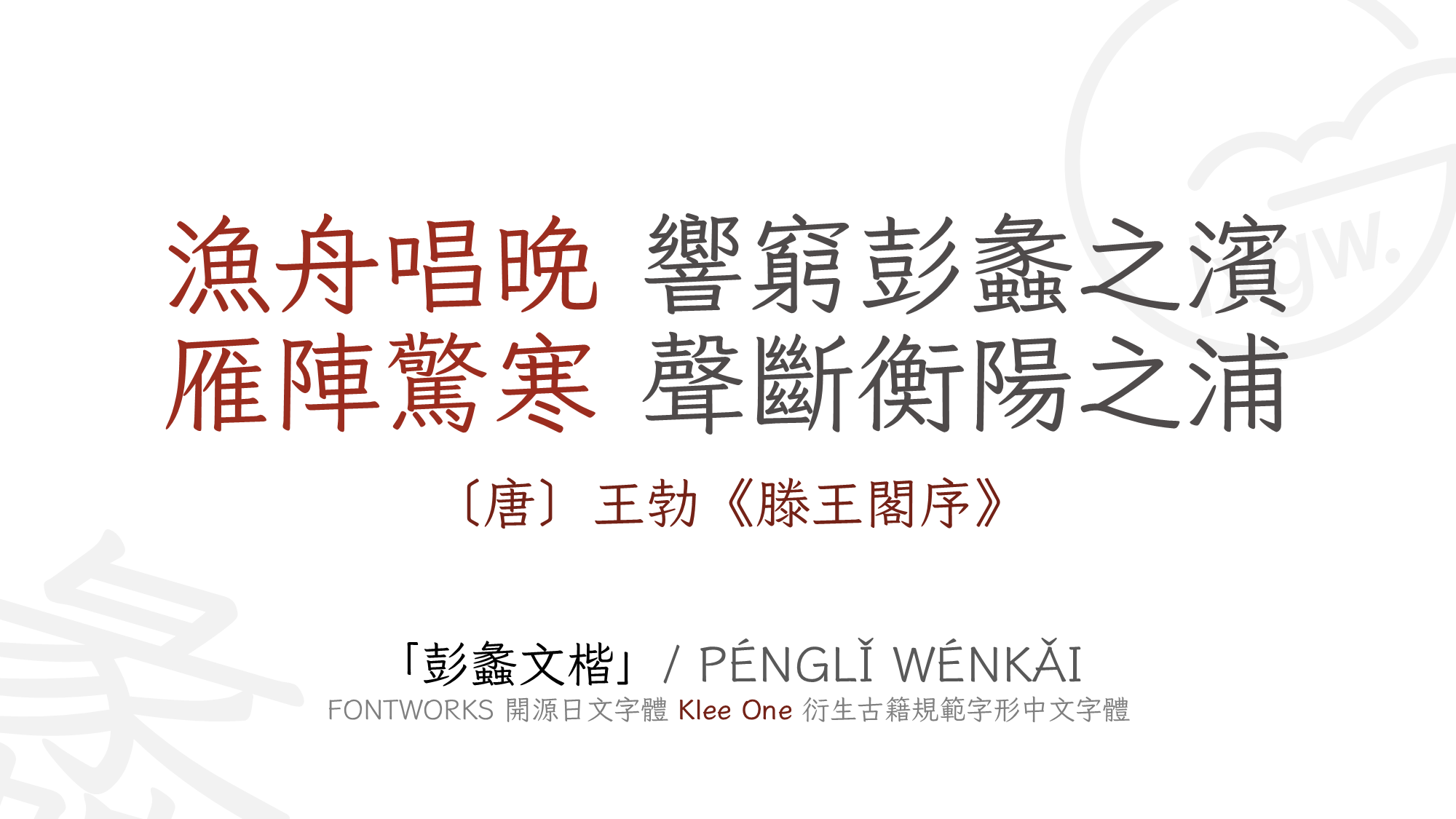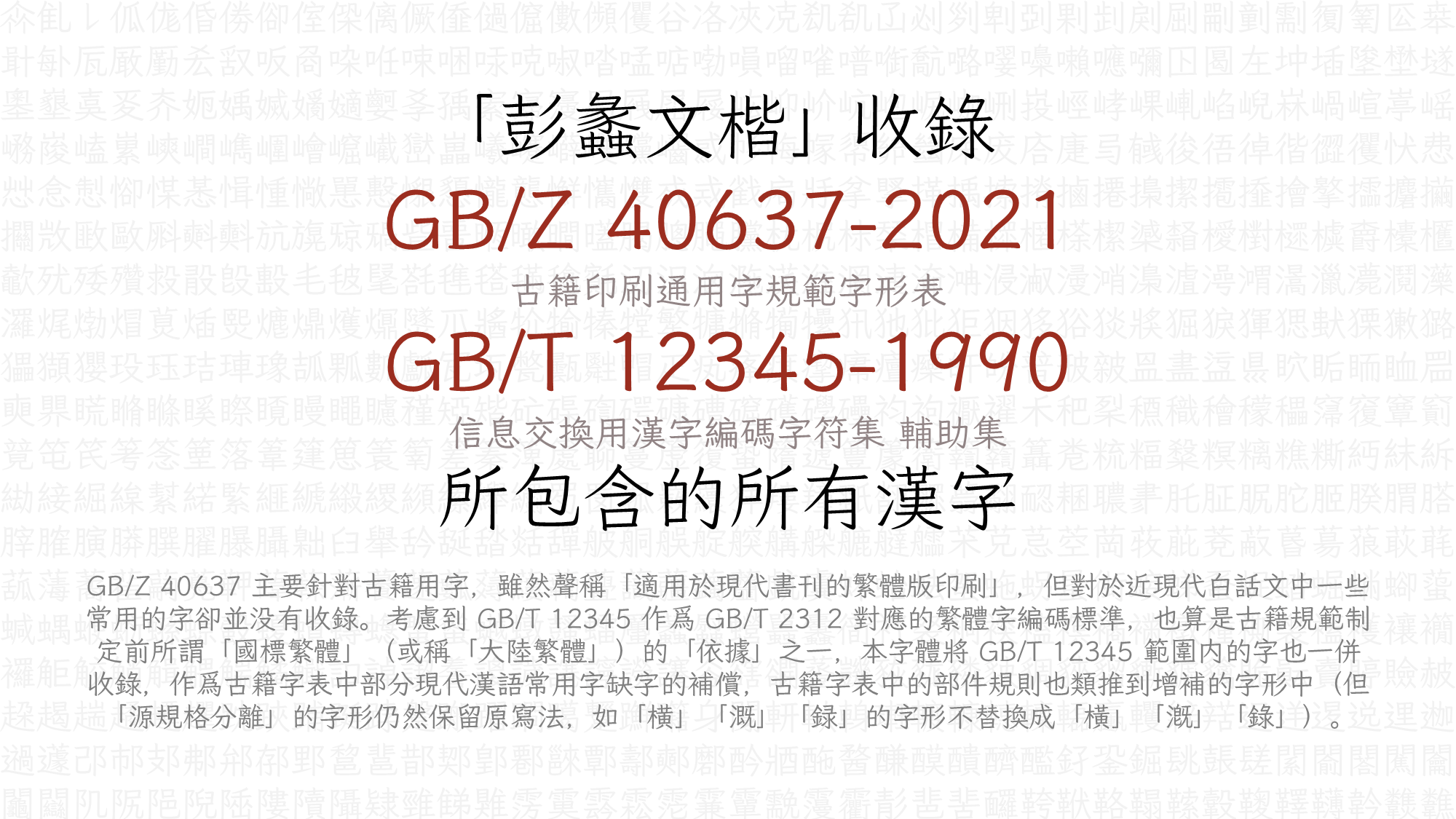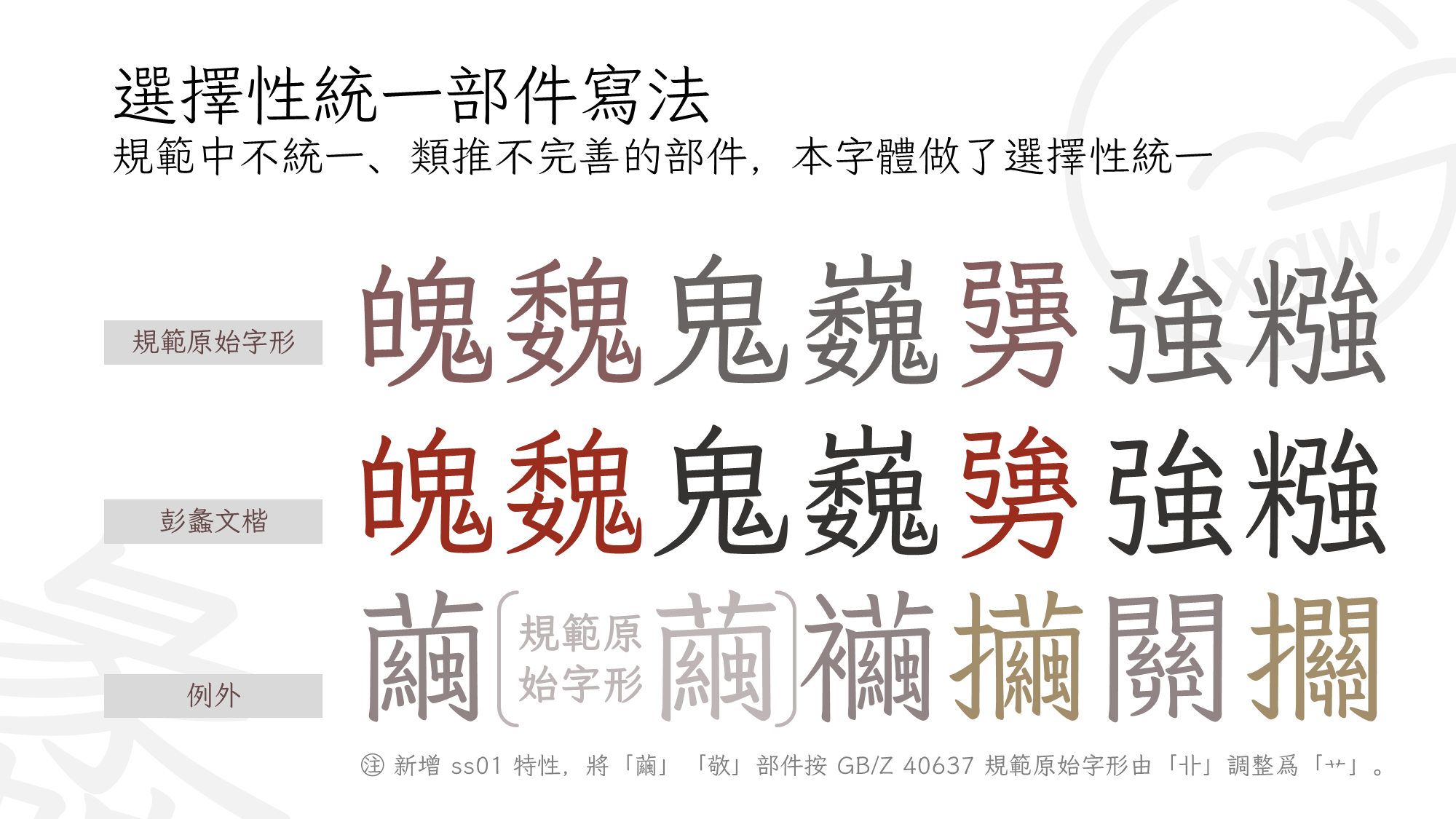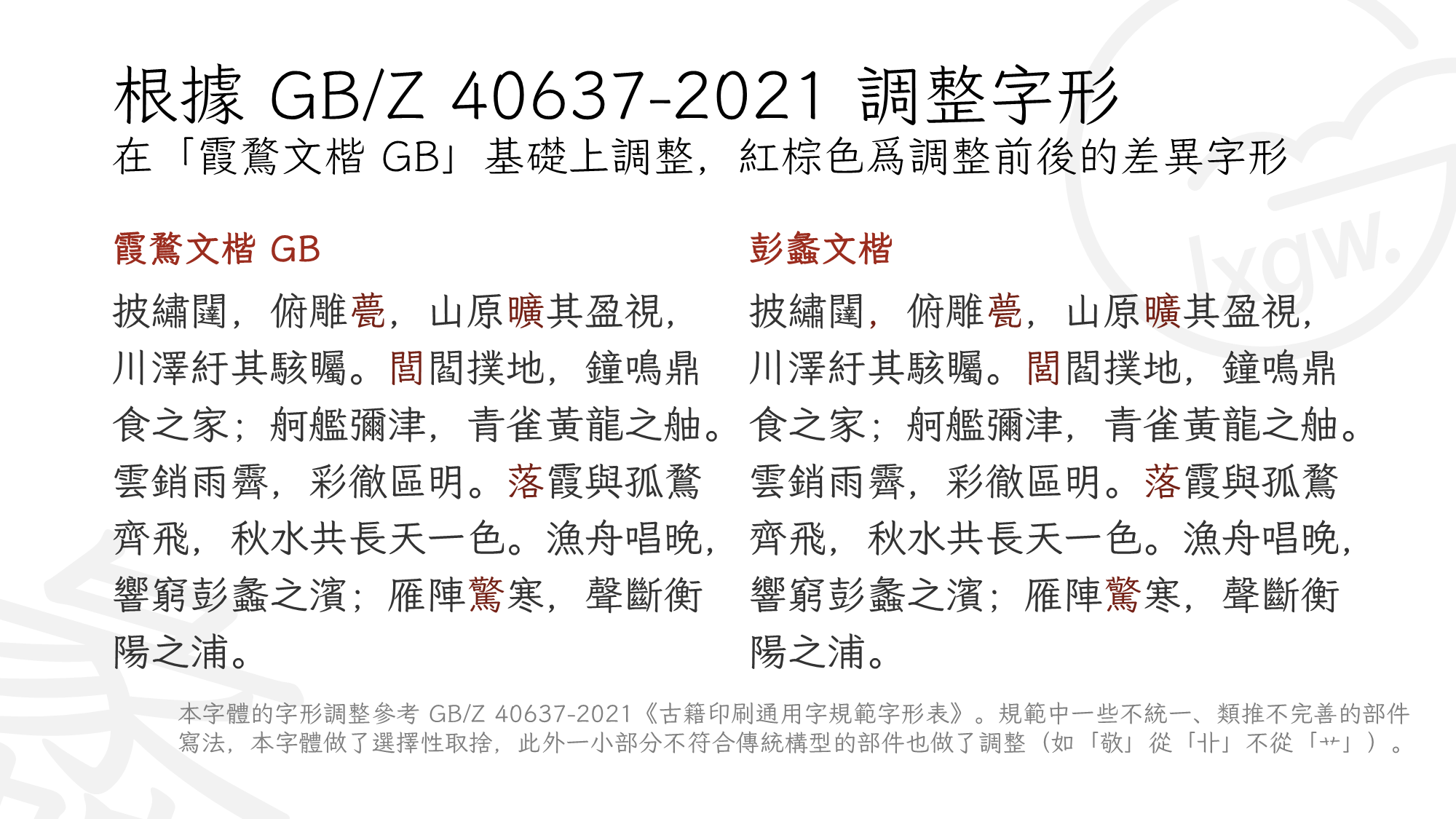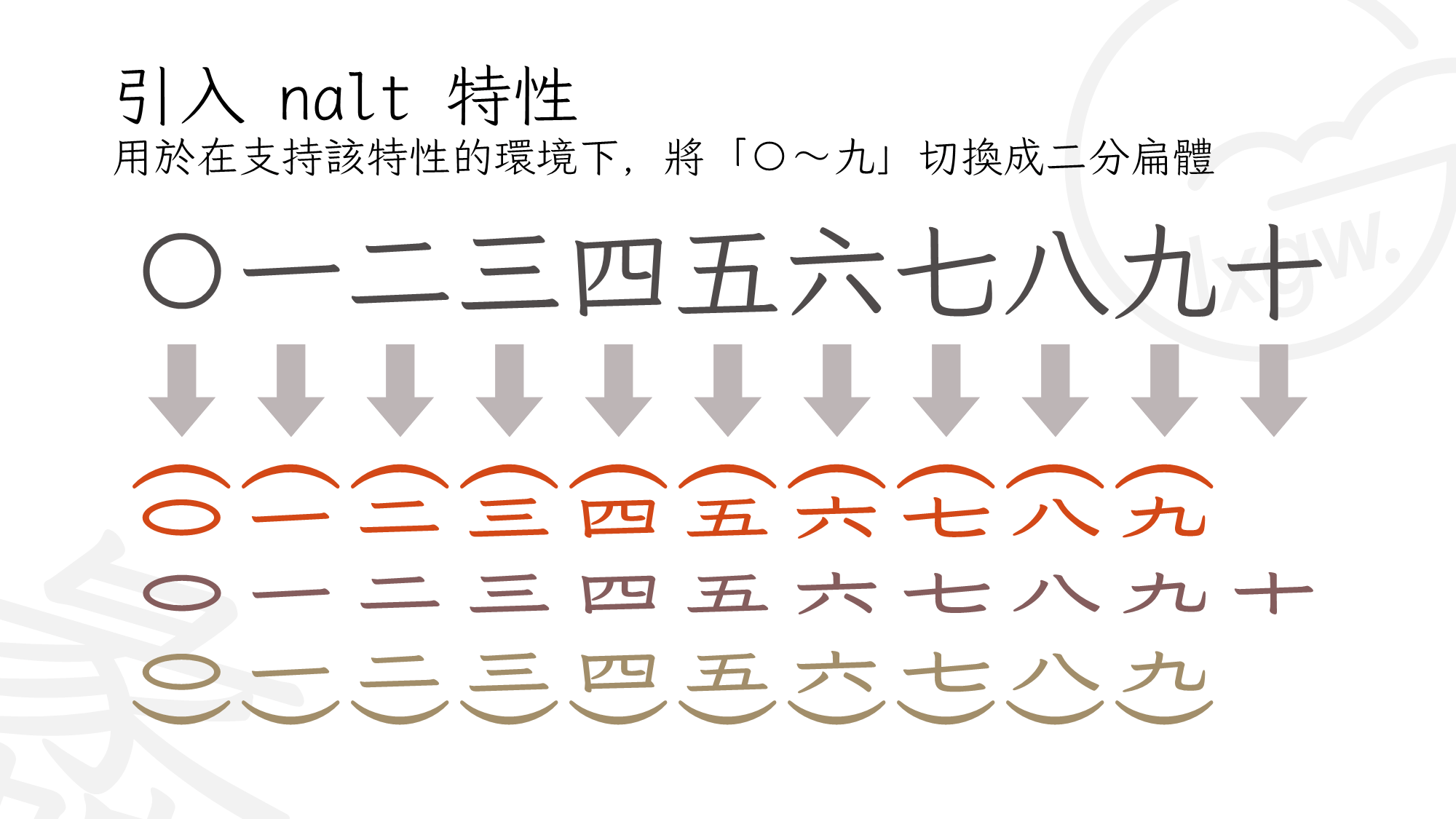
彭蠡文楷 / Pengli WenKai
基于《霞鹜文楷》系列字体衍生,参考《古籍印刷通用字规范字形表》(GB/Z 40637-2021)收字和调整字形的开源字体。
《彭蠡文楷》是基于《霞鹜文楷》系列字体衍生,根据《古籍印刷通用字规范字形表》(GB/Z 40637-2021)调整字形的开源字体,是 Fontworks(现日本蒙纳株式会社,Monotype KK)所发布的开源字体 Klee One 的三次衍生字体。
《古籍印刷通用字规范字形表》(GB/Z 40637-2021)是新中国成立以来对传世古籍印刷字的第一次整理规范,也是中国大陆第一部正式针对繁体字制定的字形规范。这部指导性技术文件声称「适用于传世古籍的印刷出版,以及现代书刊的繁体版印刷」,共收录了 14,250 个汉字字形,并提供每个字的首音和 ISO/IEC 10646 编码(涵盖 CJK 统一表意文字基本区和扩展 A、B 区)。 《彭蠡文楷》在 《霞鹜文楷 GB》 的基础上,收录 GB/Z 40637-2021 范围内的全部汉字,参考 GB/Z 40637-2021 所规定的字形进行调整,并对该规范中不统一、类推不完善的部件写法进行取舍。但愿这一开源字体项目,能为《古籍印刷通用字规范字形表》颁布后的实践贡献一份绵薄之力,为古籍印刷字体提供一种新的选择。
字体名称中的「彭蠡」一词出自〔唐〕王勃《滕王阁序》中「渔舟唱晚,响穷彭蠡之滨;雁阵惊寒,声断衡阳之浦」一句。 「彭蠡」为中国第一大淡水湖⸺鄱阳湖的古称(此外也曾作为巢湖的古称)。因「彭蠡」二字简繁无差,且与上游字体《霞鹜文楷》字体名称中的「霞鹜」二字一同出自《滕王阁序》,故本字体项目采用「彭蠡」作为名号。
「彭蠡文楷」支持 Unicode 变体序列(Unicode Variation Sequences, UVS),用于标点符号宽度和位置的选择, 点击此处查看一览表 。
• GB/Z 40637-2021 所收录的 14,250 个汉字,用于「传世古籍」所需汉字的排版与显示;
• GB/T 12345-1990 所收录的 6,866 个汉字,用于「现代书刊的繁体版本」所需汉字的排版与显示;
• Unicode 康熙部首区段所收录的 214 个部首字符,参考《康熙字典》总目中的部首字形进行取舍调整;
• 全半角 ASCII、拉丁补充-1 区、拉丁扩展 A 区、拉丁扩展 B 区、国际音标扩展区、拉丁附加扩展区、注音符号;
• 现代标点符号,以及古代汉语勾乙号「𖿢」、重文号「𖿣」;
• 易经、太玄经、算筹、中国象棋、中国传统圆形吉祥图案等符号;
• 用于古籍页码排版的二分扁体汉数字「〇~九」,通过 nalt 特性调用;
• (于 v1.005 加入)用于诗词曲联韵律标记的带圈连字「平⃝」「仄⃝」「去⃝」「入⃝」(平仄去入),通过 ccmp 特性调用,配合已经收录于 Unicode 的带圈字「㊤ U+32A4 」「㊥ U+32A5 」使用。
1. 本字体根据 GB/Z 40637-2021(下称「规范」)所规定的字形进行调整,但对于该规范中不同写法的同一部件,本字体有选择性地进行了统一(如「魄」「魏」的「鬼」部件、「勥」的「强」部件,写法分别与其他含有「鬼」「强」的字统一)。此外,规范中的一小部分不符合传统构型的部件在本字体中也做了调整,如「茧」「敬」在规范中的字形从「艹」,本字体改成了从「卝」的写法(另提供从「艹」的 ss01 字形)。
2. 规范中有少量字的字形与编码并未能很好对应:规范中收录的字形是「𣜧(⿰木茕)」,其码位应是 U+23727,但规范中给的却是「橩 U+6A69 」的编码,而 U+6A69 在 Unicode 码表中各源的字形均为「⿰木焭」。对于这种情况,本字体在按照规范将 U+6A69 做成「⿰木茕」形的同时,增加 U+23727 的码位映射。 「唧 U+5527 」同理增加 U+559E「喞」的映射。此外,规范中收录了「𨙬 U+2866C 」,但在基本区中有该字的同形重复字「邔 U+9094 」规范没有收录,本字体亦对该字形设置了双重映射。
3. GB/Z 40637 主要针对古籍用字,虽然声称「适用于现代书刊的繁体版印刷」,但对于近现代白话文中一些常用的字却并没有收录。考虑到 GB/T 12345 作为 GB/T 2312 对应的繁体字编码标准,也算是古籍规范制定前所谓「国标繁体」(或称「大陆繁体」)的「依据」之一,本字体将 GB/T 12345 范围内的字也一并收录,作为古籍字表中部分现代汉语常用字缺字的补偿,古籍字表中的部件规则也类推到增补的字形中(但「源规格分离」的字形仍然保留原写法,如「横」「溉」「录」的字形不替换成「横」「漑」「录」)。
4. 本字体不收录简化字,也不收录除拉丁、汉字和注音符号以外的其他文种(如日文假名等)。
5. 本字体只提供单字重,没有制作多字重的计划,个人认为利用机械加粗或减细的方法实现多字重意义不大,且徒增维护负担。